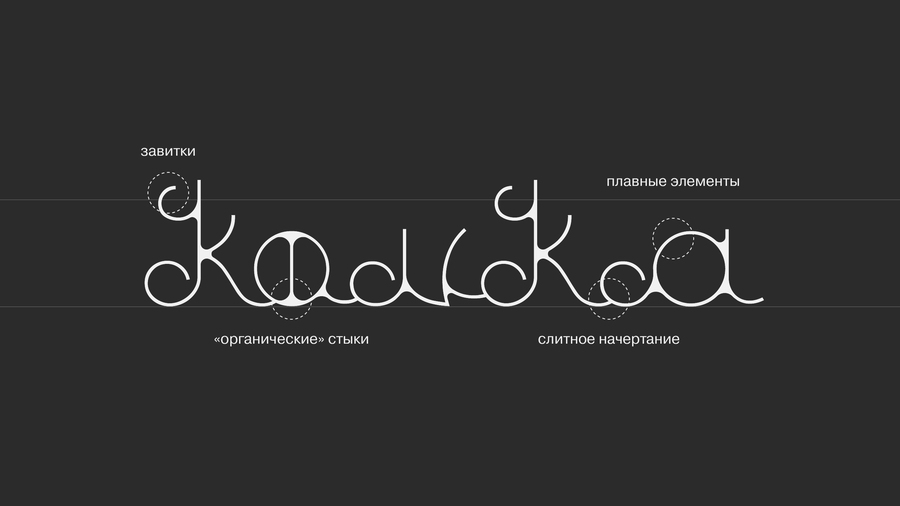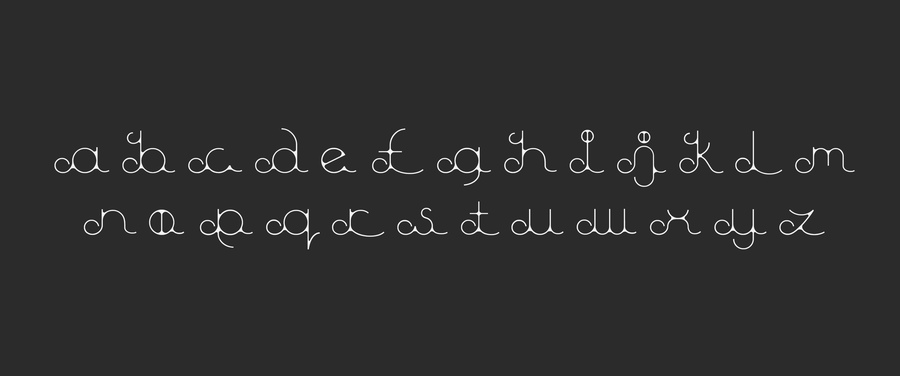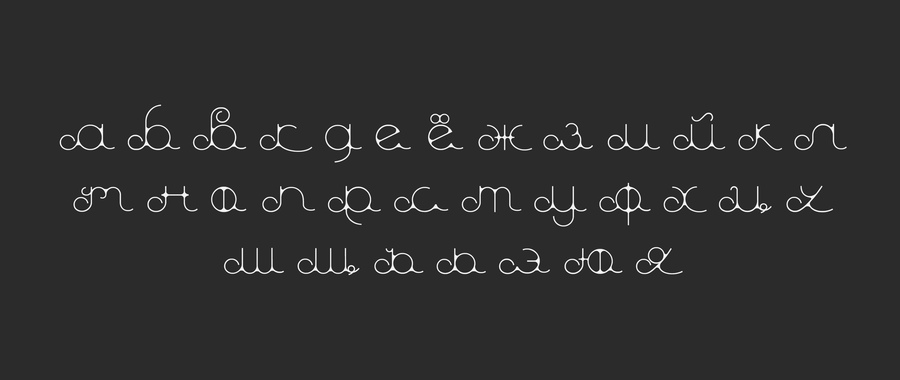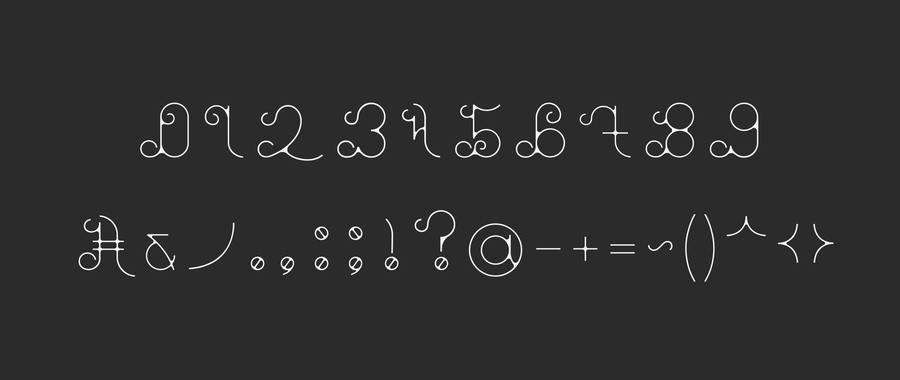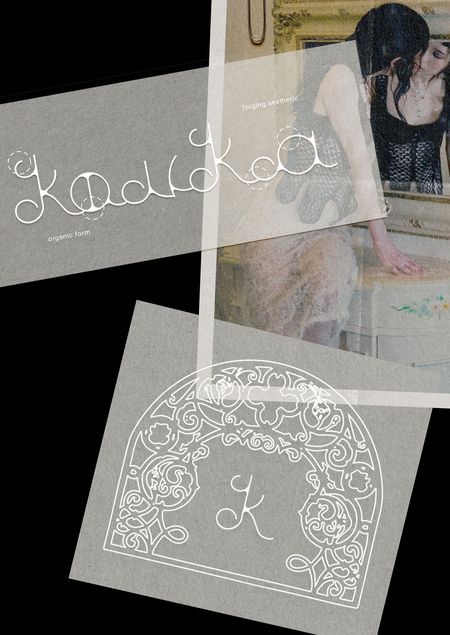
Kovka — дисплейный шрифт с слитным начертанием, вдохновлённый эстетикой ковки и металла. Отличается плавными, сопряжёнными линиями, где штрихи органично переходят друг в друга, формируя единую структуру.
Латиница
Кириллица
Специальные символы
Шрифт предназначен для Moira x Mel — ювелирного хендмейд бренда из Токио